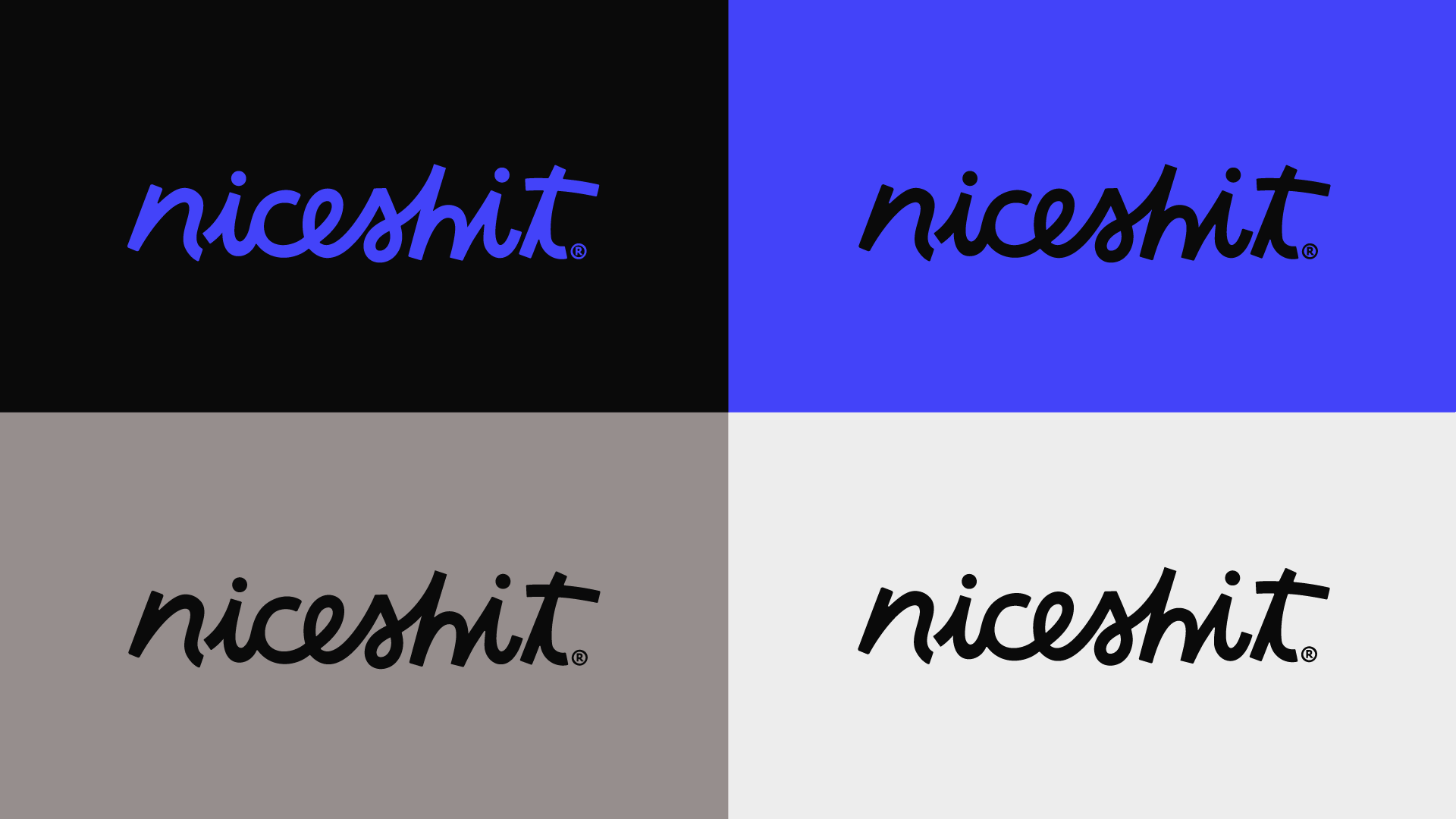
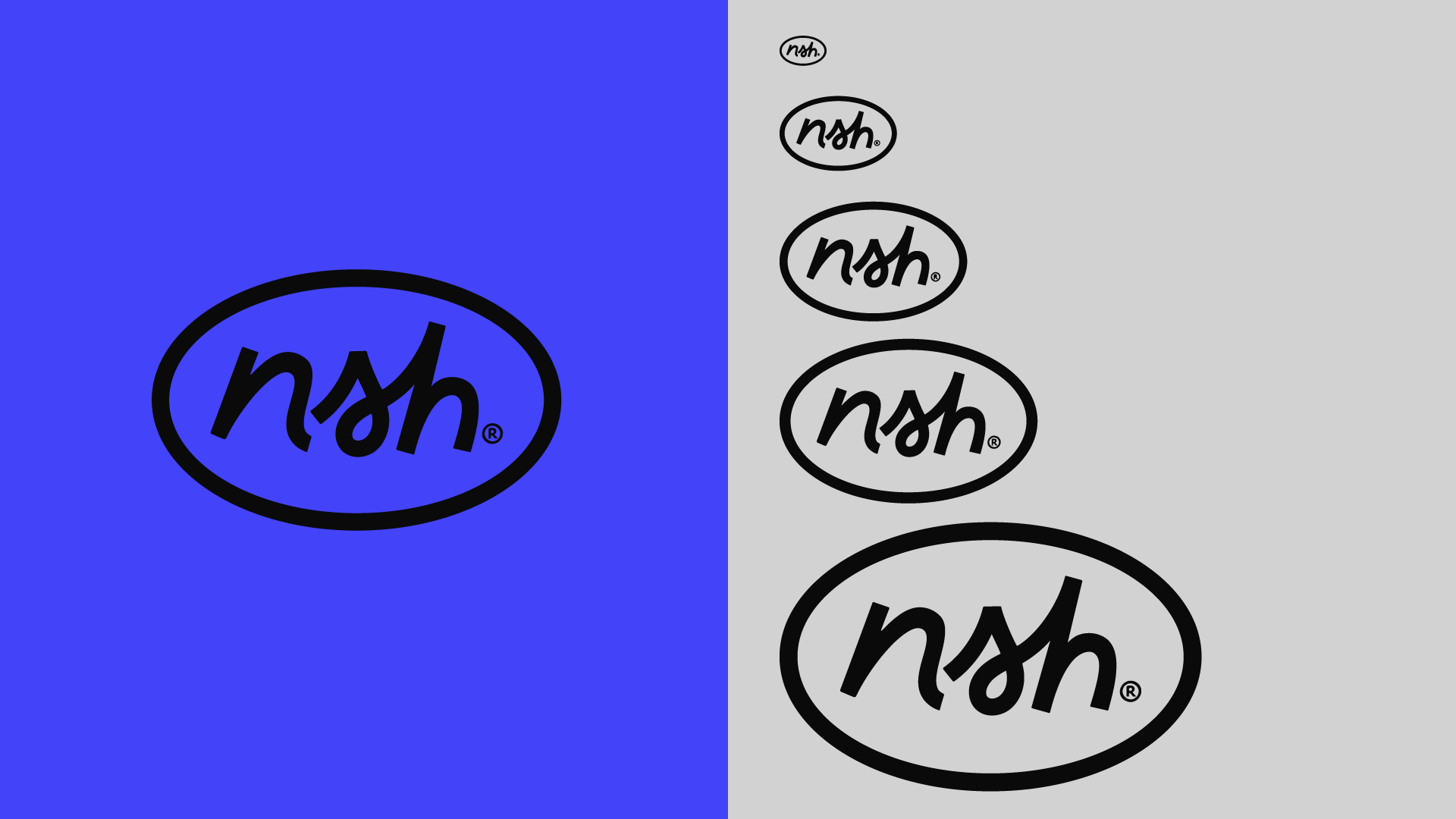
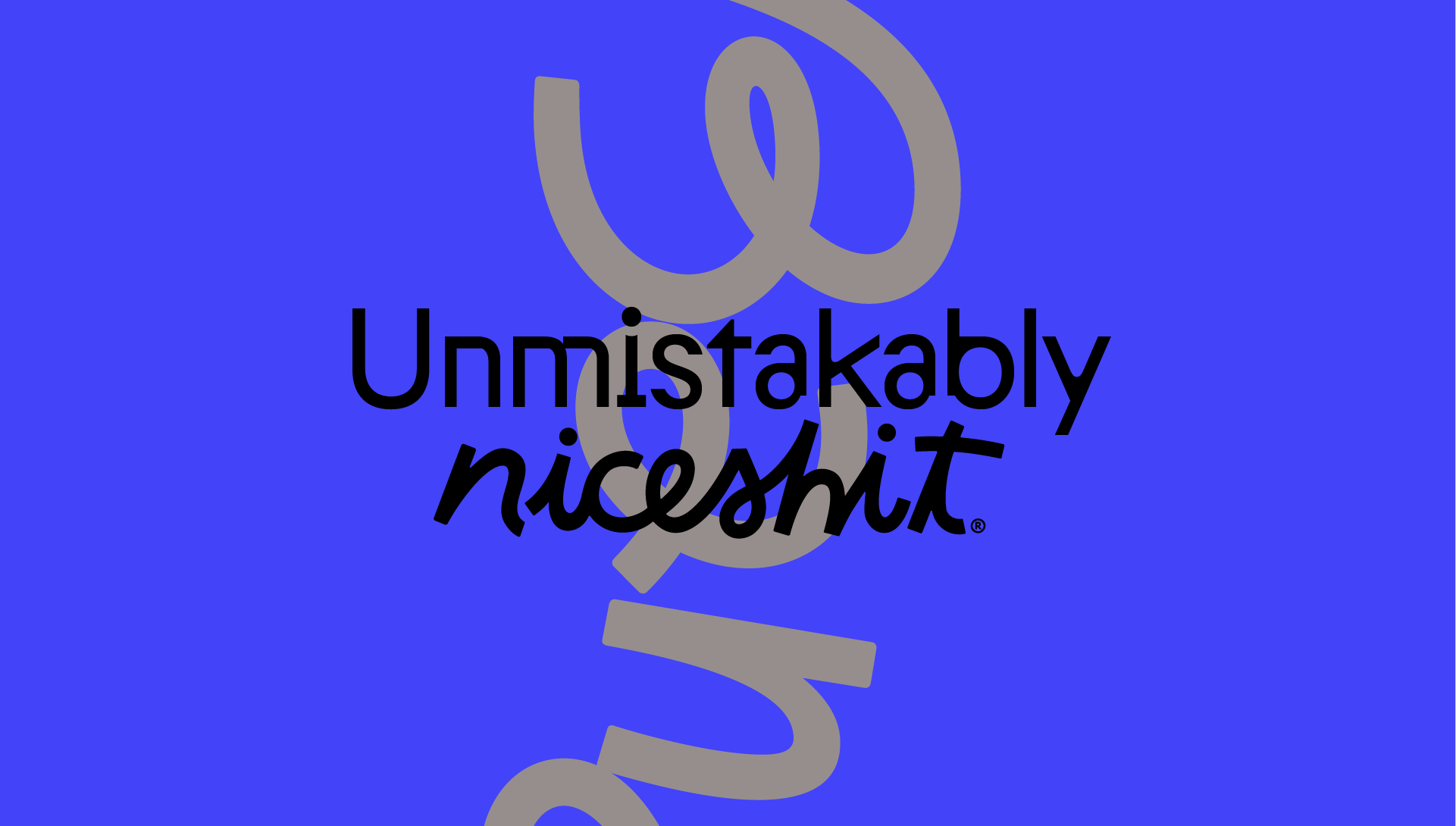
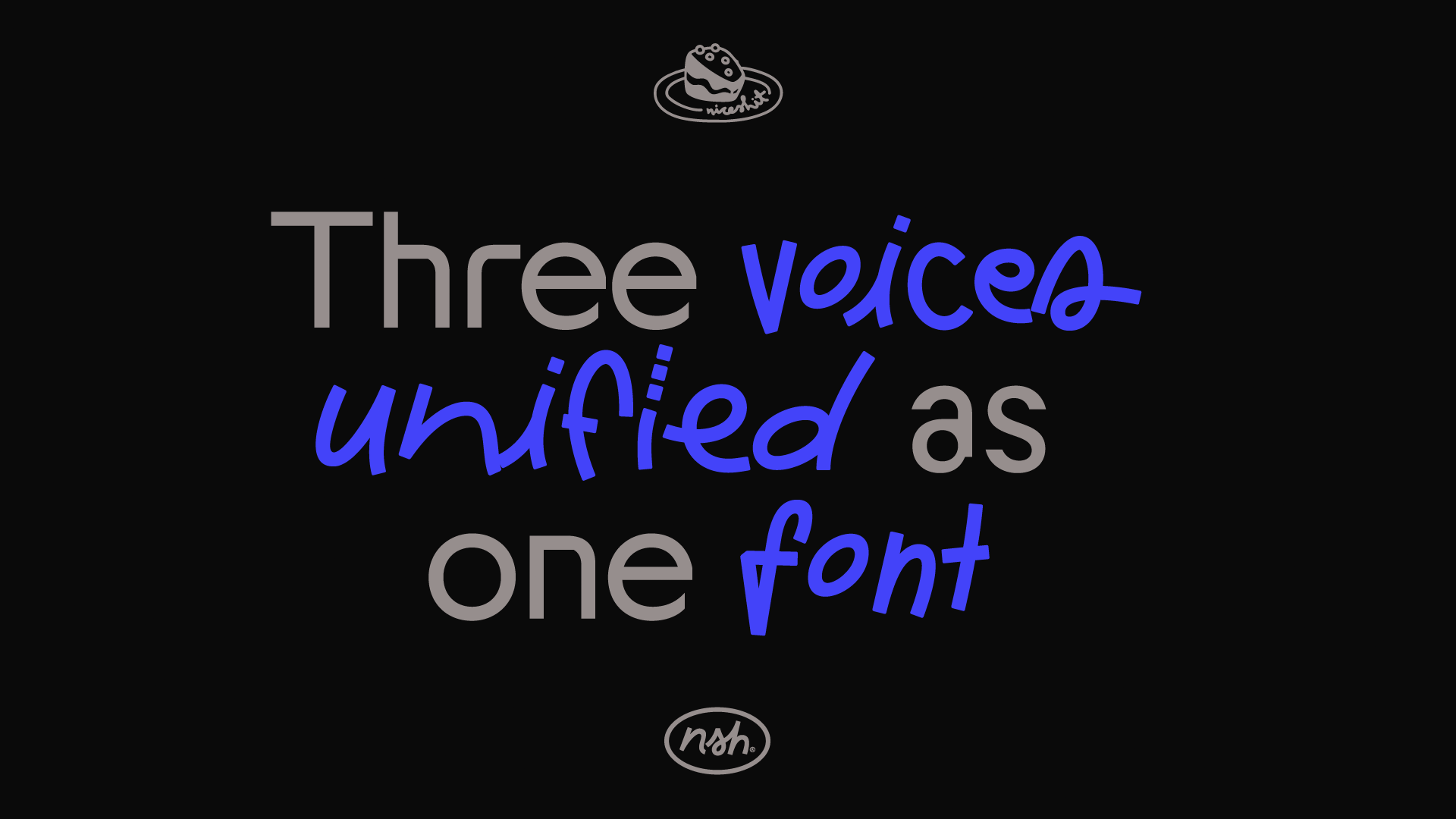
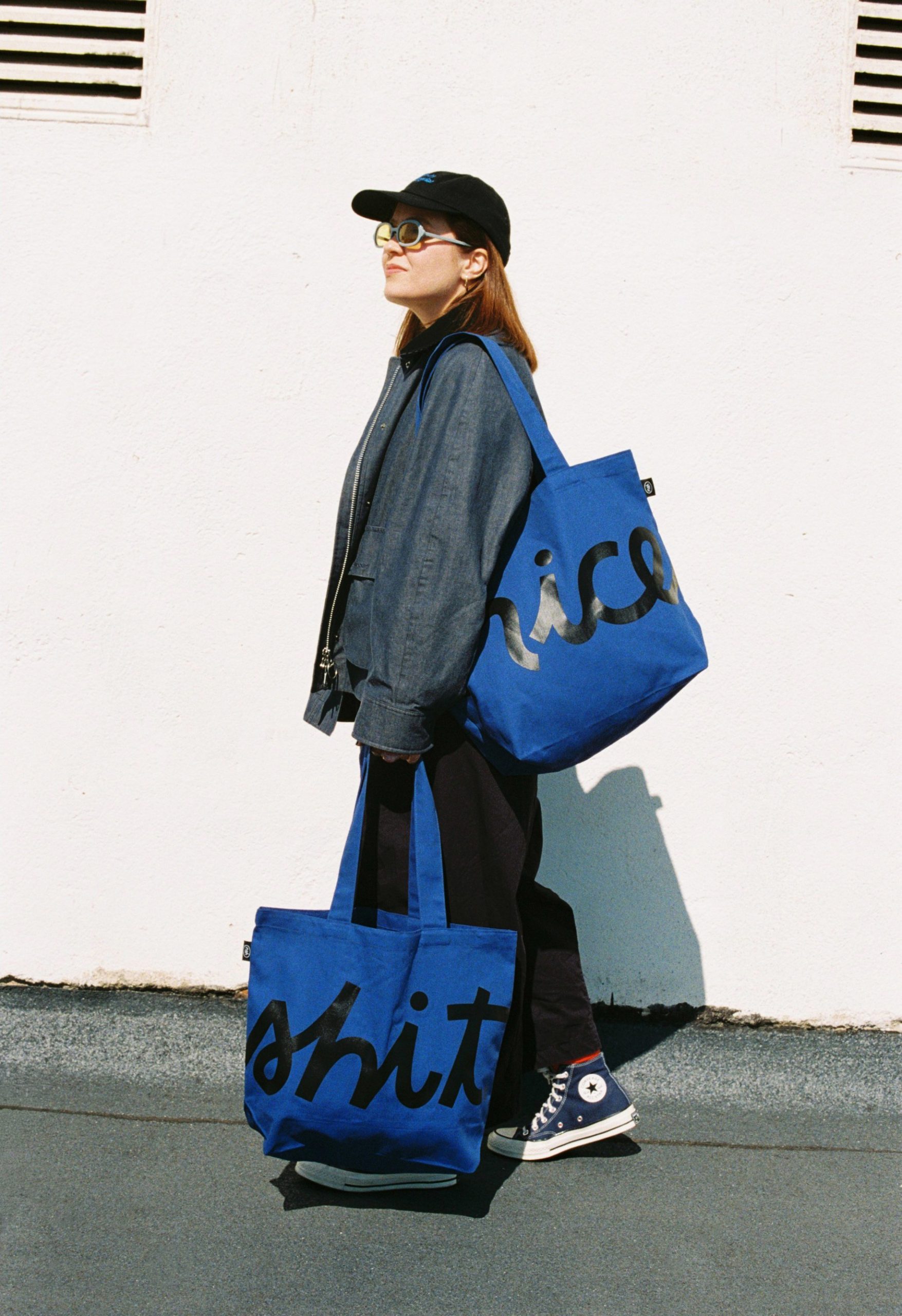
Để kỷ niệm chặng đường 10 năm đầy rực rỡ, Niceshit Studio vừa chính thức trình làng một bộ nhận diện thương hiệu mới, xoay quanh một bộ font chữ độc bản được phát triển từ chính nét chữ viết tay của ba nhà sáng lập.
Trái tim của bộ nhận diện lần này là bộ font chữ được kết hợp từ nét chữ của cả ba vị thuyền trưởng để tạo ra một phông nền làm việc chung. Đây cũng chính là hình ảnh phản chiếu chân thực cách Niceshit vận hành: hoàn toàn cộng tác, không phân chia cấp bậc, và cả ba giám đốc sáng tạo đều đồng hành trong mọi dự án từ lúc bắt đầu đến khi kết thúc.
Dự án tái định vị thương hiệu lần này bao trùm từ logo, hệ thống màu sắc cho đến typography và website, tất cả đều được xây dựng để có thể linh hoạt trên nhiều nền tảng nhưng vẫn mang đậm chất Niceshit. Với họ, “Niceshit là một thái độ, một cách tư duy và giải quyết vấn đề thông qua vô vàn phong cách và kỹ thuật khác nhau”, dựa trên ba trụ cột cốt lõi: sự đơn giản, tính hài hước và công năng.
- Font design: Fer Cozzi